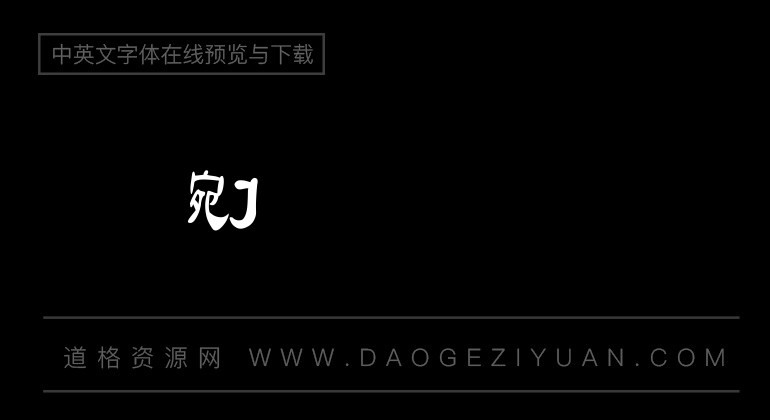
金梅新毛笔隶书
金梅新毛笔隶书是一种经典的毛笔字体,它的特点是毛笔的笔触柔和,笔画流畅,笔画粗细均匀,字形清晰,构图精美,笔锋平和,曲线优美,给人以淡雅、清新、高雅的感受。金梅新毛笔隶书字体被广泛用于书法、绘画、文字艺术等领域,是一种极具文化气息的传统毛笔字体。
金梅新毛笔隶书是一款非常不错的手写艺术字体,具有很好的视觉感,适合于文化类的宣传设计、商业类品牌的广告和产品包装设计以及个性化文字排版等较多场景。
金梅新毛笔隶书字符映射图